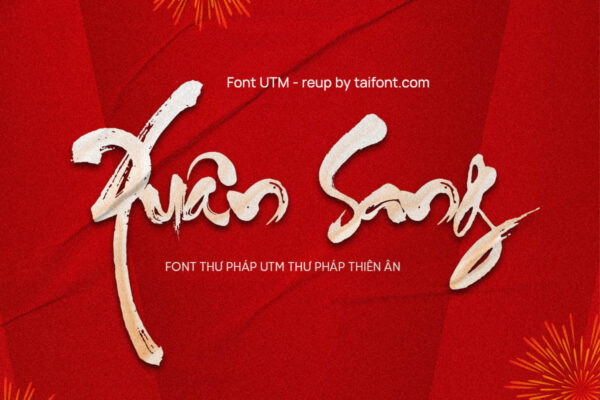
Font Việt hóa UTM Thư Pháp Thiên An – Linh hồn thư pháp Việt trong thế giới số
Trong kho tàng font chữ nghệ thuật mang đậm bản sắc dân tộc, font Việt hóa UTM Thư Pháp Thiên An nổi bật với phong cách thư pháp uyển chuyển, mềm mại nhưng đầy khí chất. Đây là một sản phẩm nằm trong bộ font UTM nổi tiếng, được Đinh Kiên thiết kế và Việt hóa một cách tỉ mỉ, mang lại trải nghiệm thị giác đậm chất truyền thống.
1. Giới thiệu về font UTM Thư Pháp Thiên An
UTM Thư Pháp Thiên An là một font chữ mô phỏng theo lối viết thư pháp tay, thường thấy trong các bức hoành phi, câu đối hay thư họa truyền thống. Nét chữ bay bổng, giàu biểu cảm, gợi nhắc đến hồn cốt của nghệ thuật viết chữ đẹp xưa kia. Với việc được Việt hóa toàn bộ, font không chỉ hỗ trợ đầy đủ tiếng Việt có dấu mà còn tối ưu cho các thiết kế truyền thông, sáng tạo mang âm hưởng văn hóa Việt.
2. Đặc điểm nổi bật của font chữ thư pháp Việt hóa này
Thiết kế thủ công, chi tiết: Các ký tự trong font được thiết kế cẩn thận, tái hiện chân thực nét cọ thư pháp, vừa tinh tế vừa mạnh mẽ.
Việt hóa hoàn chỉnh: Đinh Kiên đã Việt hóa font một cách chuyên nghiệp, đảm bảo tương thích tốt với bảng chữ cái tiếng Việt, bao gồm đầy đủ dấu và ký tự đặc biệt.
Ứng dụng đa dạng: Font rất phù hợp cho các thiết kế mang tính truyền thống như: thiệp Tết, poster văn hóa, bao bì sản phẩm thủ công mỹ nghệ, thư mời sự kiện, thiết kế logo, tiêu đề sách,…
3. Về tác giả Đinh Kiên – người thổi hồn Việt vào từng con chữ
Đinh Kiên là một trong những nhà thiết kế font Việt hóa được cộng đồng yêu thích, đặc biệt trong lĩnh vực font thư pháp. Với tâm huyết đưa văn hóa Việt Nam vào từng sản phẩm thiết kế số, anh đã đóng góp nhiều bộ font độc đáo, mang lại giá trị thẩm mỹ và ứng dụng cao.
Kết luận
Font Việt hóa UTM Thư Pháp Thiên An không chỉ là một font chữ, mà là sự kết nối giữa nghệ thuật truyền thống và công nghệ hiện đại. Nếu bạn đang tìm kiếm một font chữ thư pháp Việt hóa mang đậm dấu ấn văn hóa, đây chắc chắn là lựa chọn đáng cân nhắc trong bộ sưu tập thiết kế của bạn.
Font Việt hóa UTM Thư Pháp Thiên An – Vẻ đẹp thư pháp Việt trong từng nét chữ